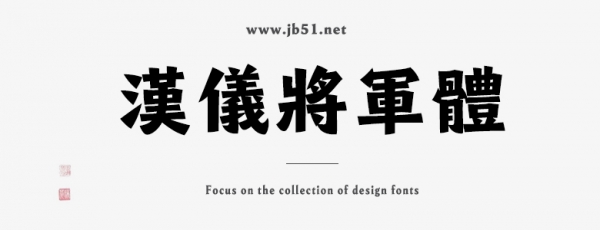
漢儀將軍簡體/繁體
漢儀將軍簡體/繁體是由漢儀字庫出品,字體字形體闊大,筆畫粗壯,莊嚴(yán)肅穆,鏗鏘有力,整體來說非常醒目且具有視覺沖擊力和震撼力,適合應(yīng)用于藝術(shù)設(shè)計、平面宣傳設(shè)計、網(wǎng)頁設(shè)計,書法字帖等領(lǐng)域,需要的朋友可以前來本站下載。